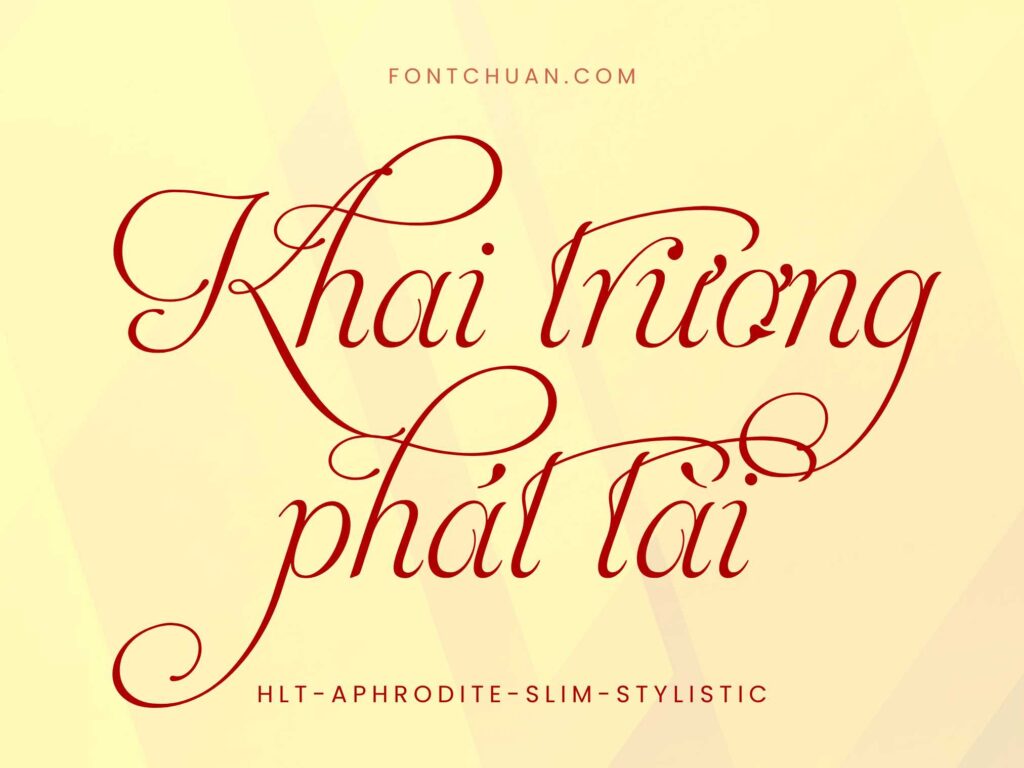
Font HLT Aphroditeslimstylistic Việt Hóa
Aphrodite Slim Stylistic là một biến thể đặc biệt của bộ font Aphrodite Slim, được thiết kế bởi Maximiliano R. Sproviero và Sabrina M. Lopez vào năm 2009. Phiên bản Stylistic này nổi bật với các ký tự trang trí tinh xảo, mang đậm phong cách thư pháp hiện đại. Với sự Việt hóa của HLT, Aphrodite Slim Stylistic hỗ trợ đầy đủ các ký tự tiếng Việt, giúp người dùng dễ dàng áp dụng trong các thiết kế đa ngôn ngữ. Thành viên của Font Chuẩn đã sưu tầm và chia sẻ font chữ này nhằm đáp ứng nhu cầu đa dạng của cộng đồng thiết kế.
Về đặc điểm thiết kế, Aphrodite Slim Stylistic sở hữu hơn 500 ký tự, bao gồm nhiều ligatures và swashes độc đáo, tạo nên sự linh hoạt và sáng tạo cho các dự án thiết kế. Font chữ này đặc biệt phù hợp cho các dự án như thiệp mời, bìa sách, poster, logo và các ấn phẩm quảng cáo, nơi cần sự tinh tế và ấn tượng mạnh mẽ. Ngoài ra, Aphrodite Slim Stylistic cũng thích hợp cho các sự kiện như lễ hội, sinh nhật, Valentine và Trung thu, mang lại không khí ấm áp và lãng mạn. Trong lĩnh vực ngành nghề, font chữ này được ứng dụng rộng rãi trong quảng cáo, thiết kế thiệp cưới, giáo dục và công nghệ, góp phần tạo nên sự độc đáo và thu hút cho các sản phẩm và thương hiệu.